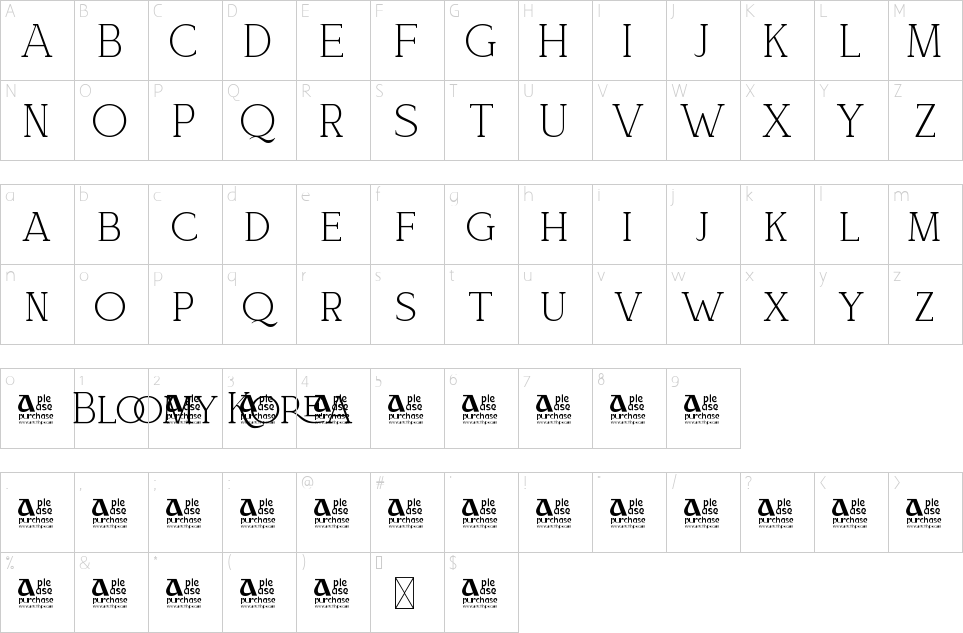
Aqui está uma descrição em português do Brasil, envolvente e natural, para a página de download da fonte ‘Bloomy Korea Font’, seguindo as regras fornecidas: Descubra a riqueza visual da cultura coreana com a fonte Bloomy Korea. Desenvolvida pelo estúdio Artchitype Studio, essa bela fonte oferece um toque de sofisticação e modernidade para seus projetos digitais. Bloomy Korea é perfeita tanto para uso personalizado quanto para criações gráficas profissionais. Seja em seus projetos de design editorial, sites ou logotipos, ela trará uma aura única que remete à cultura coreana sem comprometer o equilíbrio estético da sua produção. Esta fonte é especialmente indicada para quem deseja incorporar elementos contemporâneos ao seu trabalho. Com 687 downloads até agora, acredite quando dizemos que ela já faz parte de uma coleção crescente de designers apaixonados por sua qualidade e versatilidade. Descubra hoje mesmo o encanto da cultura coreana em suas criações digitais através desta fonte. Não perca mais essa oportunidade para adicionar um toque especial a seus projetos, seja profissionais ou pessoais.